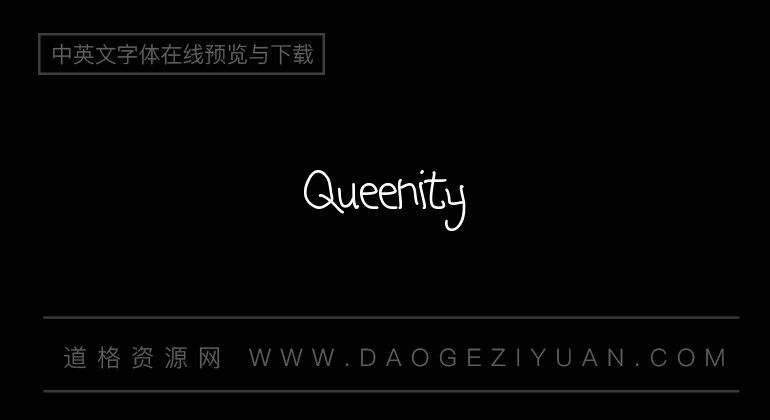
Queenity
Queenity字体是一款新颖的视觉设计字体,它具有流畅、清新、大气的特点。该字体由荷兰设计师Yuri Gordon设计,它采用了古典的曲线来设计,保留了传统字体的细节,同时又增加了一些现代风格的元素,使其看起来更加时尚大气。Queenity字体可以用于商业广告、标志、海报、报纸、杂志等设计中,是一款非常适合用于多种设计的字体。
Queenity是一款非常不错的手写艺术字体,具有很好的视觉感,适合于文化类的宣传设计、商业类品牌的广告和产品包装设计以及个性化文字排版等较多场景。